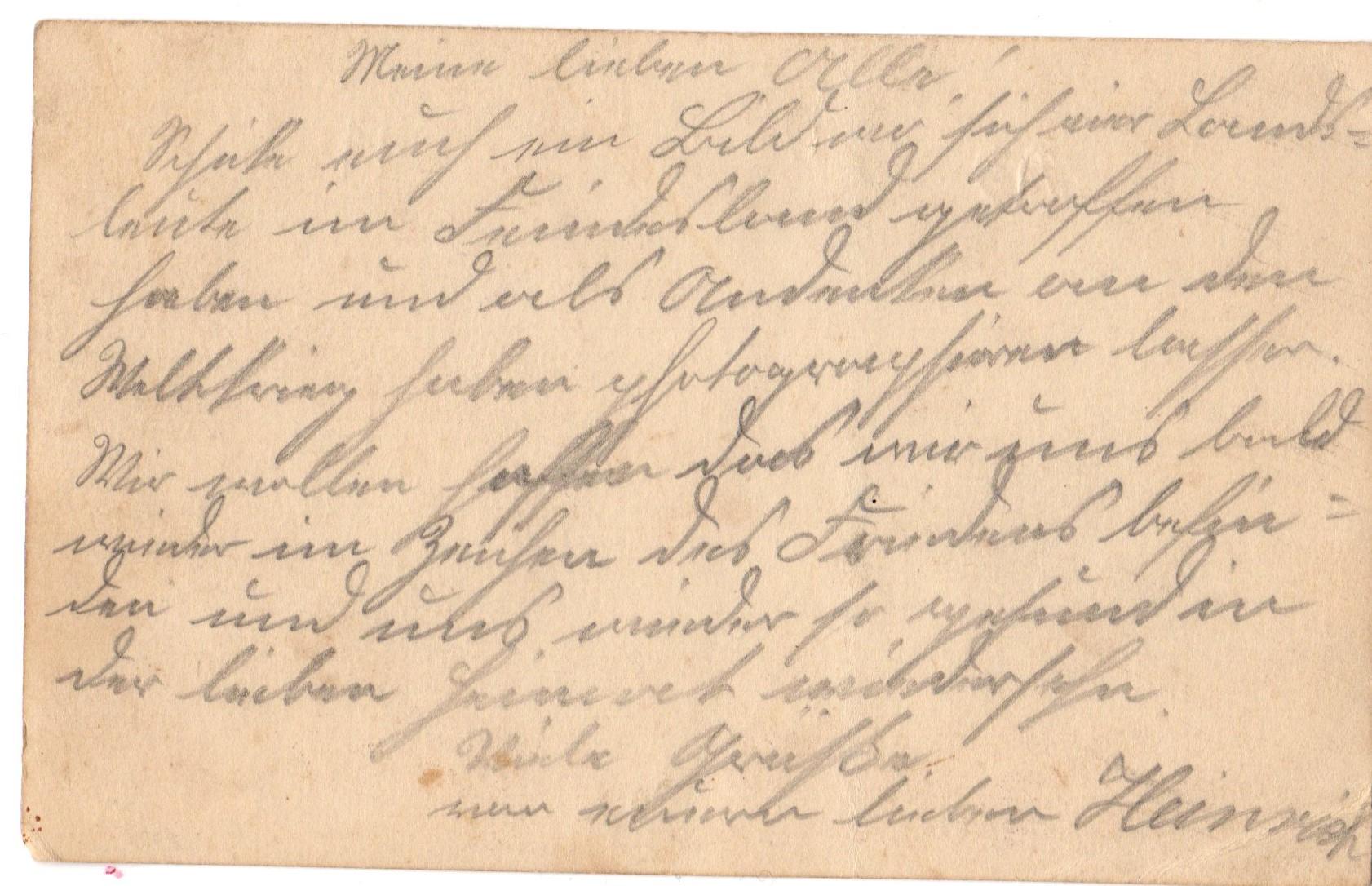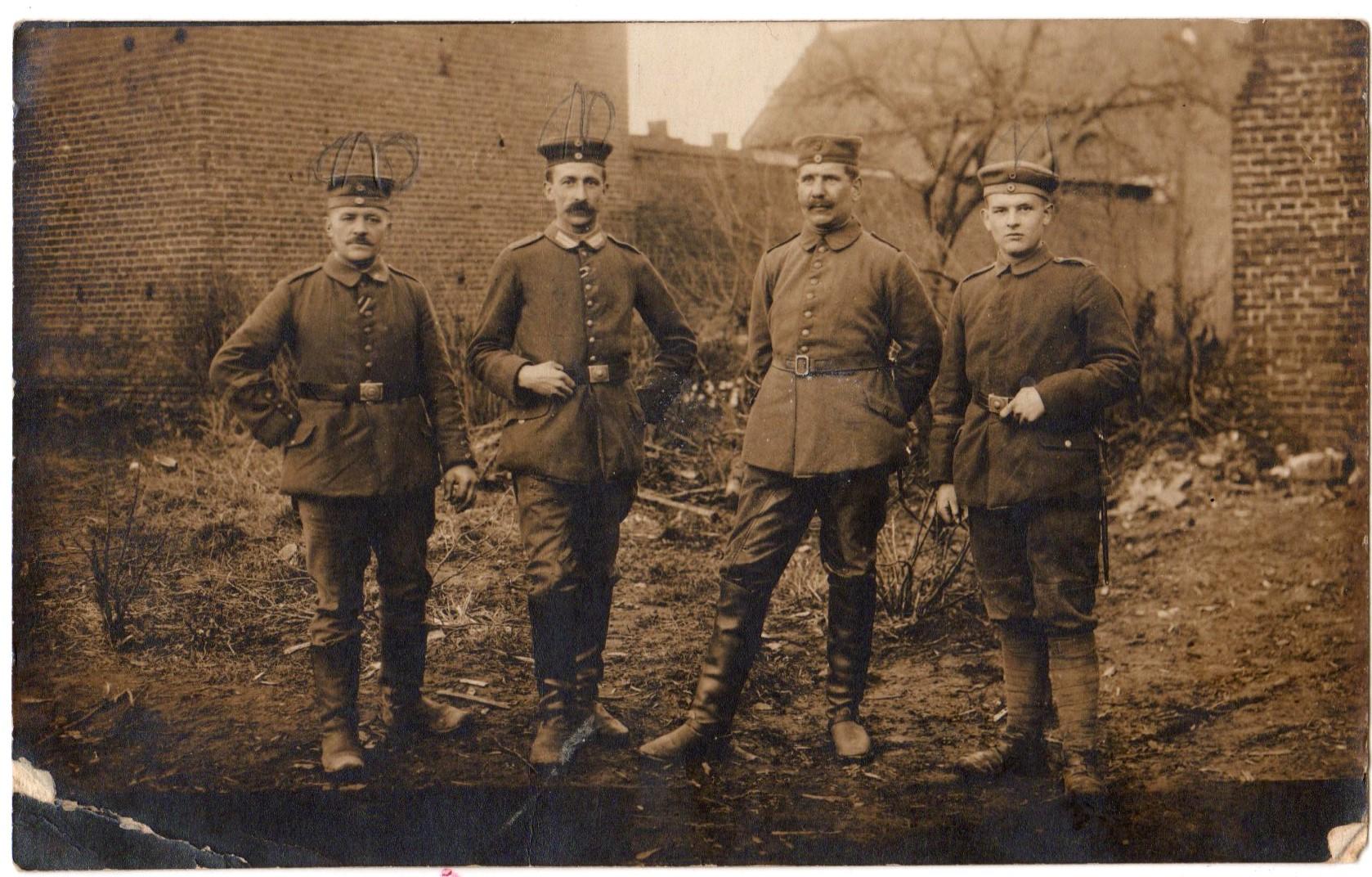
alte Handschrift / Sütterlin lesen
ich hoffe hier kann mir jemand weiterhelfen. Ich habe einen alten Brief gefunden. Schätze mal 1. Weltkrieg. Genau weiß ich es leider nicht. Nur würde ich gerne aus Interesse wissen was da steht. Ich kann diese Art von Schreibschrift leider nicht lesen. Habe es auch versucht zu entschlüsseln aber da komme ich leider an meine Grenzen. Hat hier vielleicht irgendjemand eine Idee, wie ich am Besten weiter vorgehe oder an wen ich mich wenden könnte? Oder kann vielleicht jemand diesen Brief entschlüsseln? Ich wäre für jede Hilfe dankbar!
Meine lieben Alle!
Schicke euch ein Bild [] sich [] Lands-
leute im Feindesland getroffen
haben und als Andenken an den
Weltkrieg haben photographieren lassen.
Wir wollen hoffen das wir uns bald
wieder im Zeichen des Friedens befin-
den und uns wieder so gesund in
der lieben Heimat wiedersehn.
von eurem lieben Heinrich
Im ersten Satz bin ich ein wenig unsicher. Muss es eventuell "wie sich vier Landsleute" heißen? Vielleicht kommt man auch weiter, wenn das Foto, von dem hier die Rede ist, noch erhalten ist.
das ist eine deutsche Current. Die Sütterlin war die aufrechte Lernform mit größerer x-Höhe. Leider ist der Brief irgendwie sehr schwer zu lesen ... Eine schulische Sütterlin wäre sicher einfacher gewesen ... so es nicht so was wie meine Sauklaue wäre ...
Meine lieben ?????,
Schicke euch im ????? .... ???? Lands-
leute im Feindesland ge?????????
haben und als Andenken an der
W????????? haben fotografieren lassen-
Wir wollen hoffen das mir und b???s
????? im Zeichen der Freundschaft befin-
den und uns wieder so gesund  in
der lieben h??????? wiedersehen.
von ?????? lieben Heinz
Ich dachte an einen verrutschten i-Punkt; der Punkt gehört aber, wie ich nun sehe, zum Ausrufezeichen drüber. "Wo" ist ein guter Vorschlag. Ich habe überhaupt gezweifelt, dass es sich um ein "w" handelt; aber wenn man sich die anderen Wörter mit "w" anschaut, könnte es schon hinkommen.
Vielen Dank für eure Antworten. Hab hier mal die Vorderseite mit geschickt. Ich denke der Name Heinrich ist schon richtig und nicht Heinz. Vielleicht ist es jetzt schlüssiger?